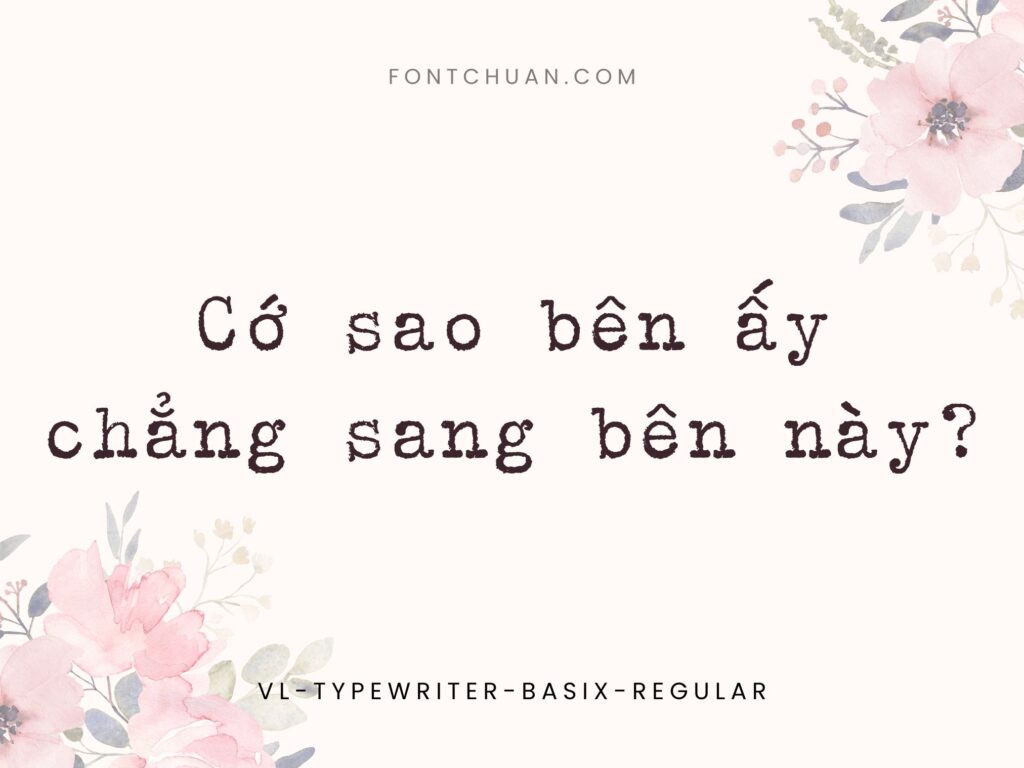
Font VL Typewriter Basix Trọn Bộ Việt Hóa
Tác giả Font: Matthias Luh
VL-Typewriter-BasiX là một Font Monospace mang phong cách serif cổ điển, được thiết kế bởi Matthias Luh. Phông chữ này tái hiện lại hình ảnh của những máy đánh chữ xưa, mang đến cảm giác hoài niệm và mộc mạc. VL-Typewriter-BasiX đã được Việt hóa bởi Việt Linh, hỗ trợ đầy đủ các ký tự tiếng Việt, giúp người dùng dễ dàng ứng dụng trong nhiều dự án sáng tạo. Đây cũng là một Font chữ giáo dục phù hợp cho tài liệu học tập, sách tham khảo hoặc các dự án nghiên cứu, nhờ khả năng hiển thị rõ ràng và ổn định. Phông chữ này được thành viên Font Chuẩn sưu tầm và đăng tải nhằm phục vụ nhu cầu thiết kế đa dạng.
Với thiết kế đậm chất cổ điển, VL-Typewriter-BasiX phù hợp cho các ứng dụng như tiêu đề, văn bản dài, thiết kế logo và các ấn phẩm in ấn. Trong lĩnh vực sự kiện, phông chữ này có thể được sử dụng trong các dịp như lễ hội, thiệp cưới và sinh nhật. Ngoài ra, VL-Typewriter-BasiX cũng thích hợp cho các ngành nghề như quảng cáo, giáo dục và công nghệ.